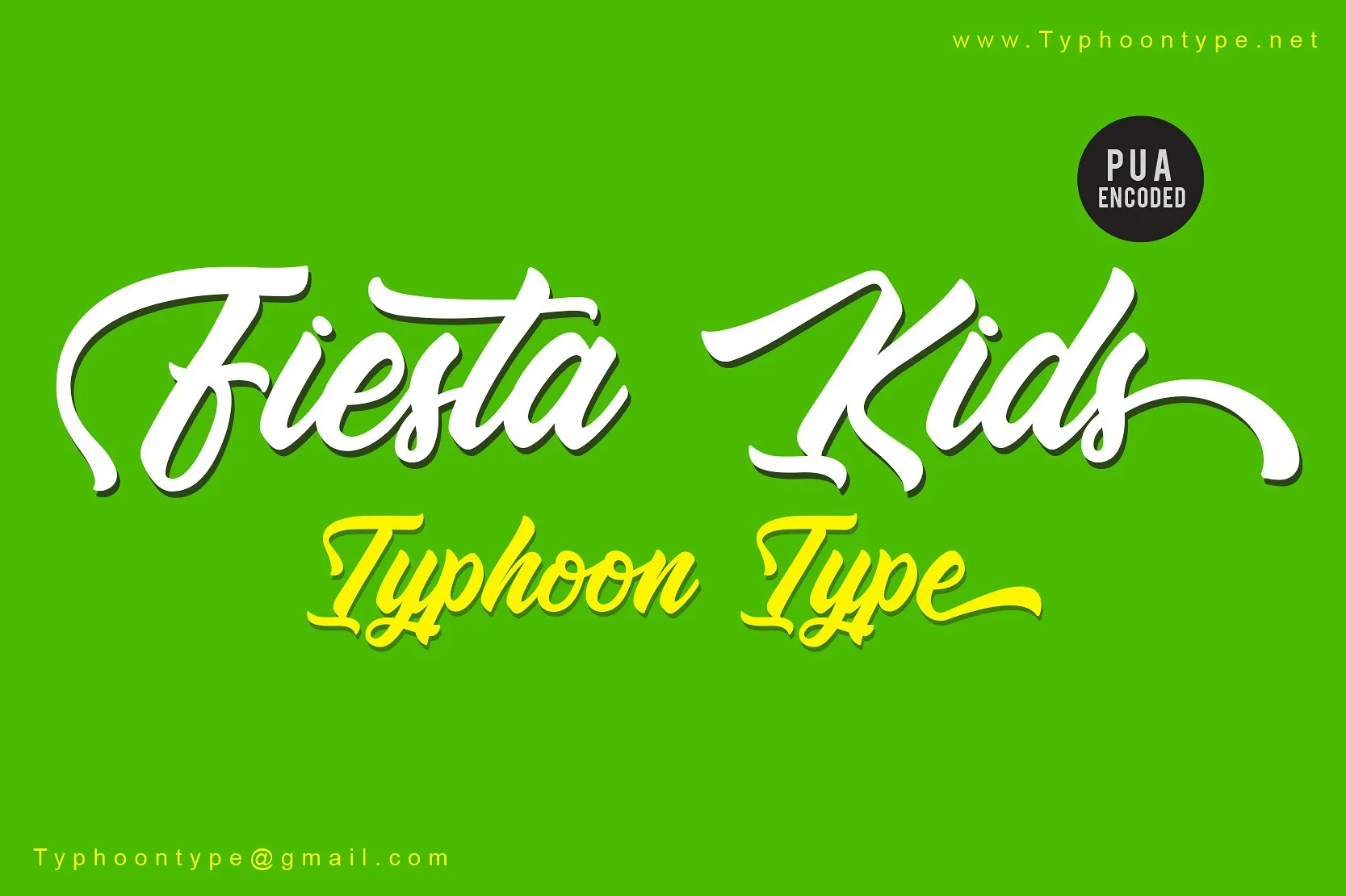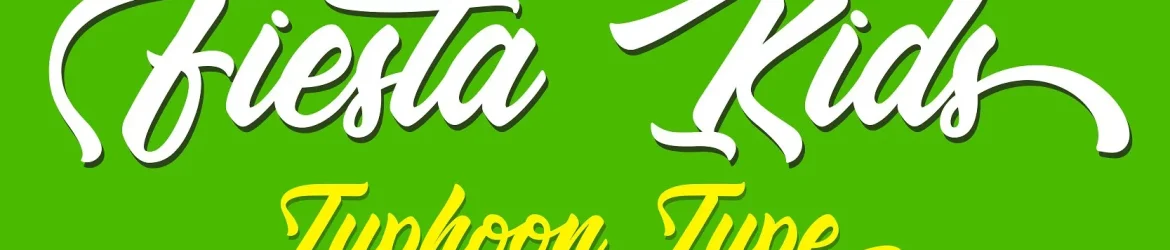
Fiesta Kids Script Font – Download Grátis
Olá! Introduzimos a Fiesta Kids Fonte ! Esta é uma nova e encantadora fonte de traço para criar designs belos e elegantes. Feita especificamente para atender às suas necessidades, esta fonte se destaca por seu charme único. Através desta criação do designer M.0Type, você encontrará a perfeição em logos, etiquetas de nome, anúncios, embalagens de produtos, roupas, mídia social e cartões de felicitações. Seja para ilustrar qualquer projeto visual ou personalizar seus materiais promocionais, a Fiesta Kids Fonte está aqui para ajudá-lo a dar um toque especial em seu design.